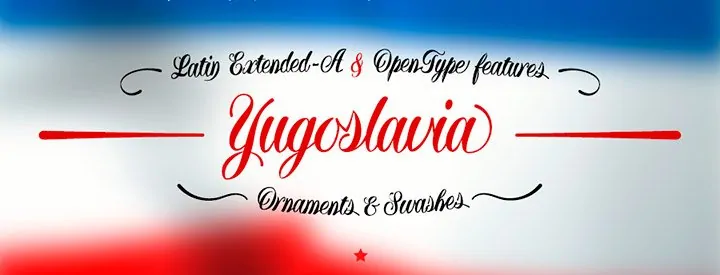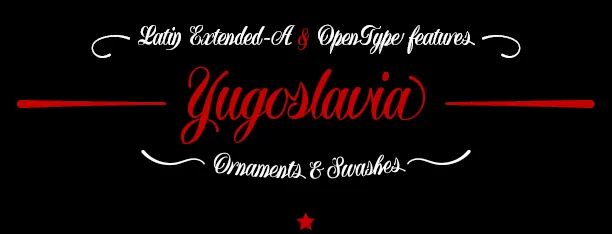
Elegante fuente caligráfica realizada con pluma e inspirada en las tipografías clásicas concatenadas surgidas en el S XIX y que siguen vigentes hasta hoy.
La fuente incluye un juego completo de minúsculas con florituras (swashes) para uso al final de palabras, además, un juego de 8 ornamentos reversibles para remate y decoración de frases y 3 trazos de diferentes estilos para subrayar y adornar títulos.
Esta fuente es ideal para diseñar tarjetas de felicitación o bodas, invitaciones, diplomas, etc. donde se busque un estilo clásico, lujoso o elegante y que a su vez transmita al diseño tradición e historia.
Tipografía manuscrita clásica
Proporción: Regular
Funciones OpenType: Additional languages, All Alternates, Denominators, Discretionary Ligatures, Extended Fractions, Historical Forms, Historical Ligatures, Inferiors, Kerning, Localized Forms, Numbers Small Caps, Numerators, Oldstyle Figures, Ordinals, Ornaments, Scientific Inferiors, Slashed Zero, Standard Ligatures, Subscript, Superior letters, Superiors, Superscript, Swash, Terminal Forms, Titling alternates.
La fuente «Yugoslavia» dispone en su versión comercial de un juego de 590 glifos (Latin Extended-A), con soporte para cualquier idioma europeo o centro europeo. Yugoslavia font también incluye funciones OpenType (Compatibles con InDesign, QuarkXpress, Photoshop e Illustrator.